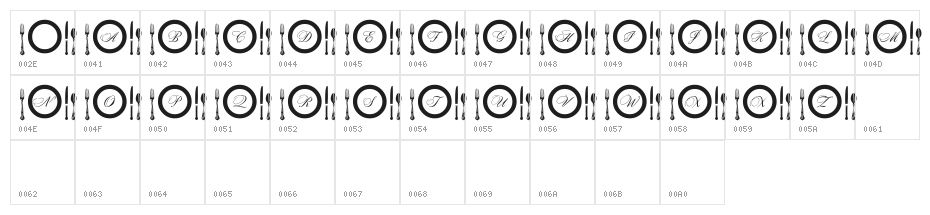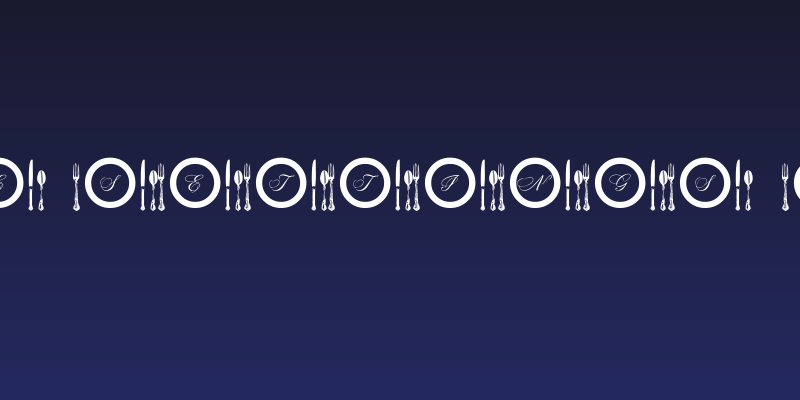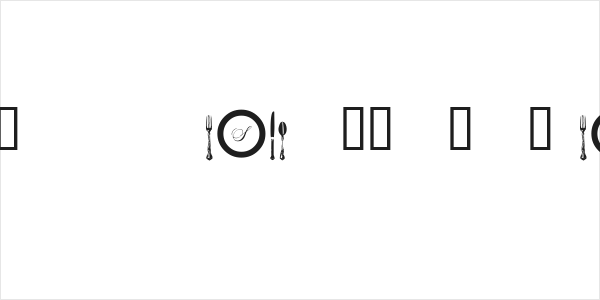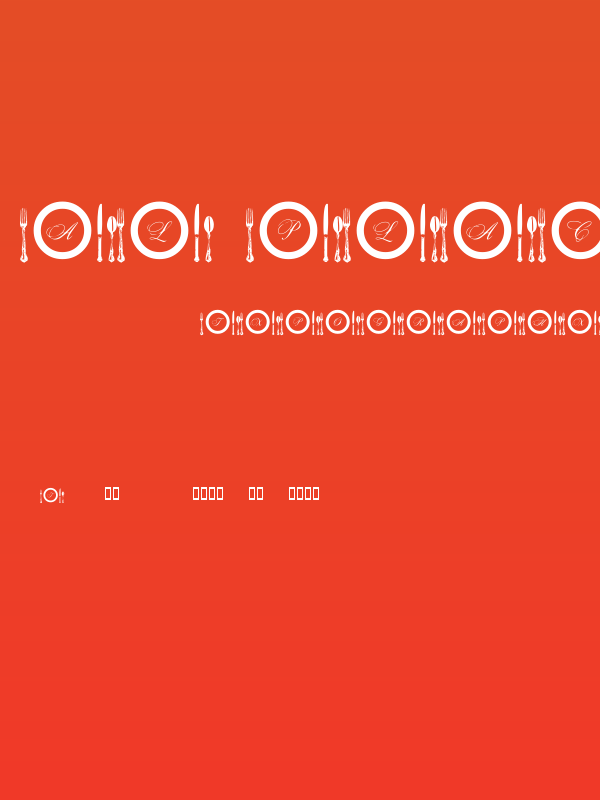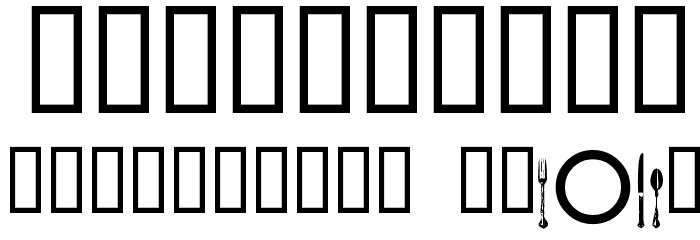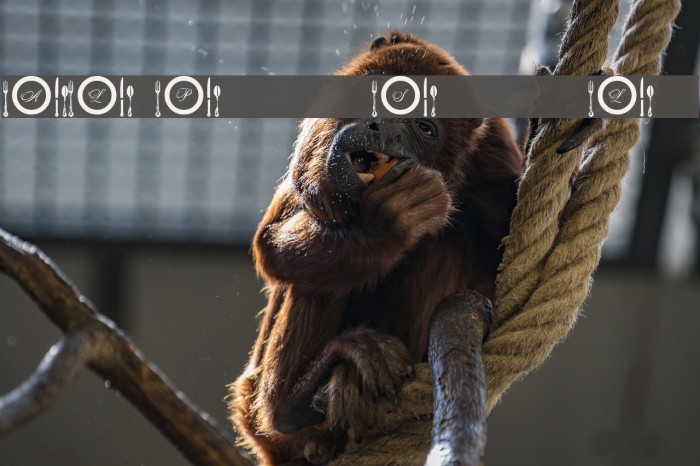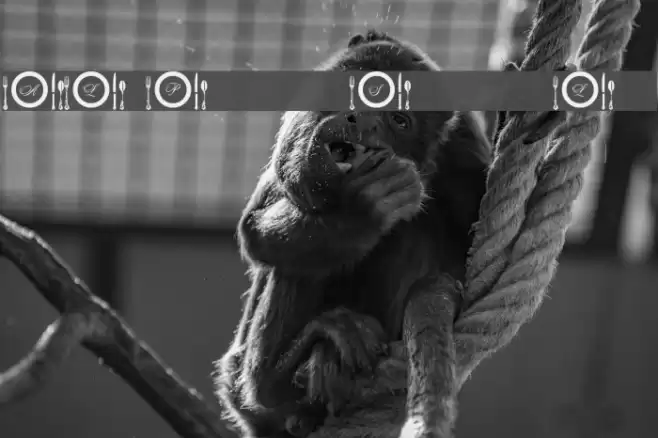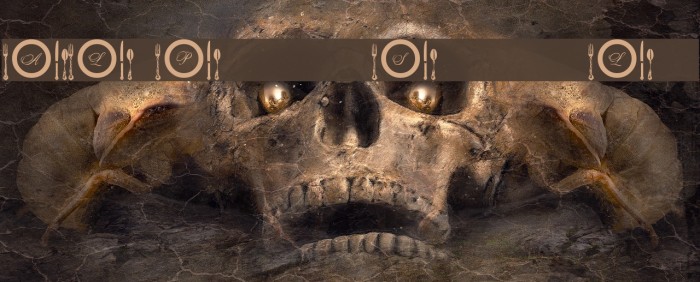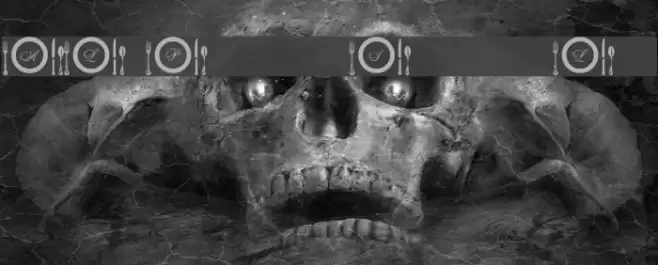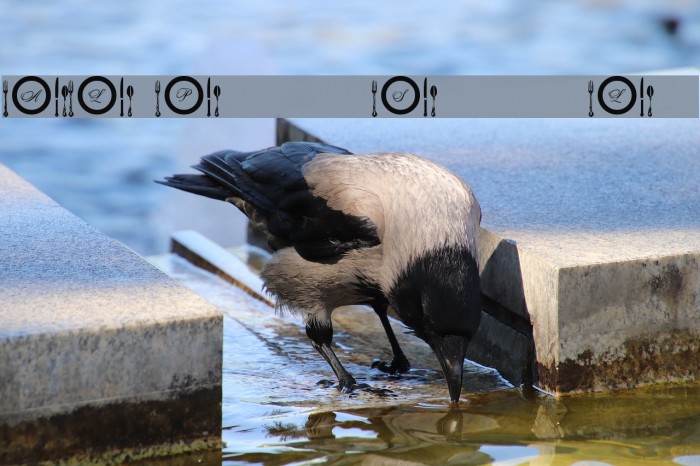
AL Place Settings Letters Font
| Style général | Modern, Decorative |
| Cas d'utilisation | Logos, Headlines, Thematic Designs |
| Projets proposés | Ideal for restaurant branding, menu designs, food blogs, and culinary event invitations. |